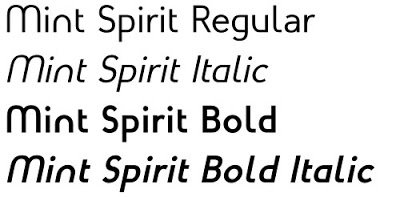
Mint Sprint, il nuovo font targato Linux Mint
Il team Linux Mint ha realizzato un proprio font denominato Mint Sprint il quale molto probabilmente arriverà di default sulla prossima Linux Mint 12 Lisa rendo portando la Distribuzione ad avere una maggior propria identità. Il nuovo font Mint Sprint è stato realizzato inspirandosi ai font Futura, Gillius, NeoGothis e Ubuntu cercando di creare un nuovo font chiaro, moderno e bello.